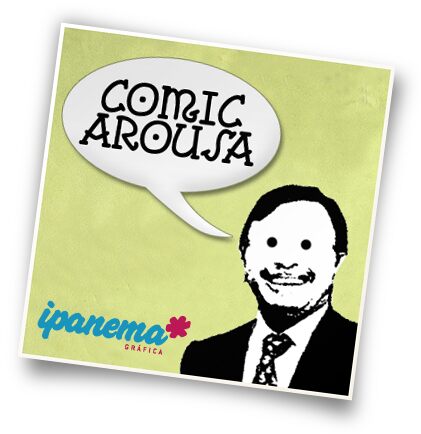
Comic Arousa von CC License ist eine kostenlose Comic-Schrift, die mit ihrem handgezeichneten, märchenhaften Schwung besticht. Die Buchstaben wirken weich und verspielt, mit abgerundeten Strichen, kräftigen Kurven und kleinen, geschwungenen Details, die dem gesamten Schriftbild einen leicht frechen Rhythmus verleihen, ohne die klare, freundliche Form zu verlieren.
Sie passt perfekt auf Kinderbuchcover, Klassenzimmer-Poster, Partyeinladungen, Comic-Titel oder verspielte Verpackungen, bei denen ein kostenloser Font eine warme, lebendige Note braucht. Da die Formen groß, rund und leicht schrullig sind, eignet sich Comic Arousa am besten für kurze Überschriften, Namen und Zitate, bei denen die beschwingte Persönlichkeit für sich selbst sprechen kann.
Comic Arousa